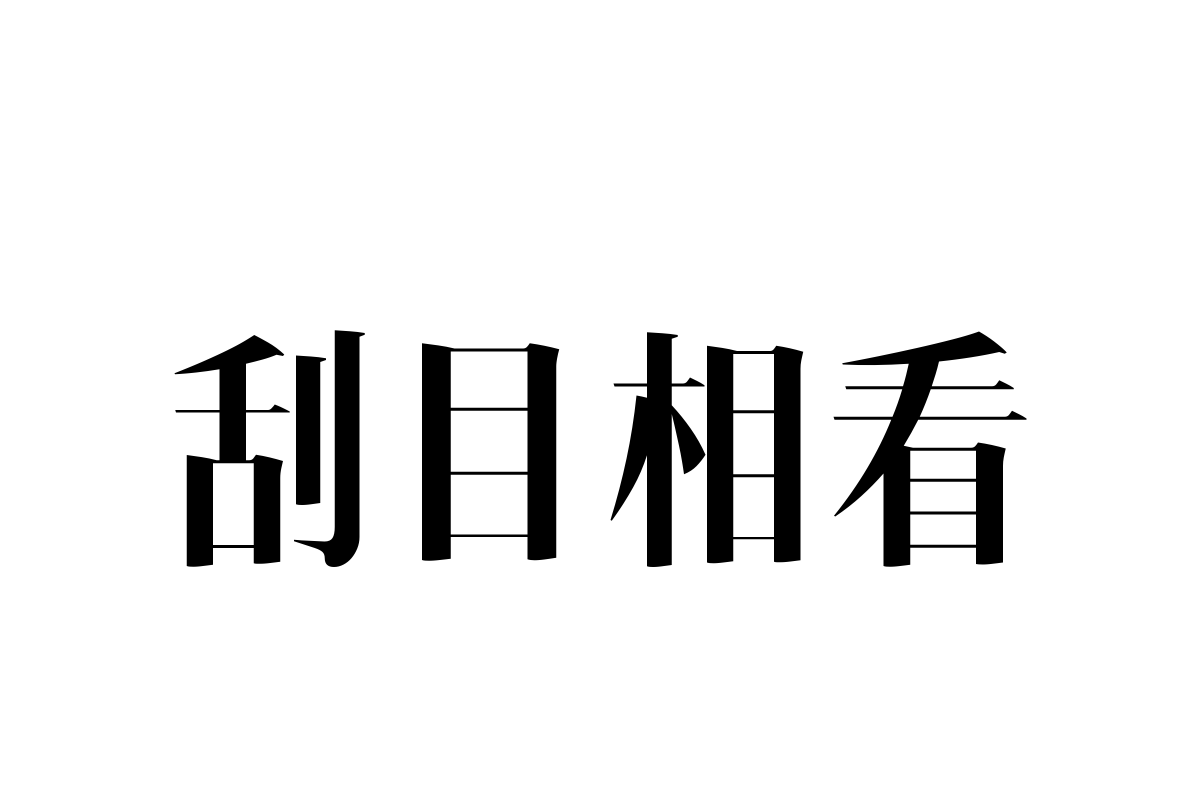
汉仪瑞意宋X_75W 是一款现代的中文字体,由汉仪公司设计。这款字体的特点是笔画流畅、字形优美,适合用于各种需要书写或印刷的场合。它的设计灵感来源于传统的书法艺术,但又融入了现代的设计元素,使得字体既有传统韵味又不失时尚感。
这款字体的特点包括:
– 笔画流畅:字体的每一个笔画都经过精心设计,使得书写时更加流畅自然。
– 字形优美:字体的字形经过精心调整,使得整体看起来更加美观大方。
– 适合多种场景:无论是用于书籍、海报、广告还是其他印刷品,汉仪瑞意宋X_75W都能展现出其独特的魅力。
总的来说,汉仪瑞意宋X_75W是一款非常优秀的中文字体,值得大家尝试使用。